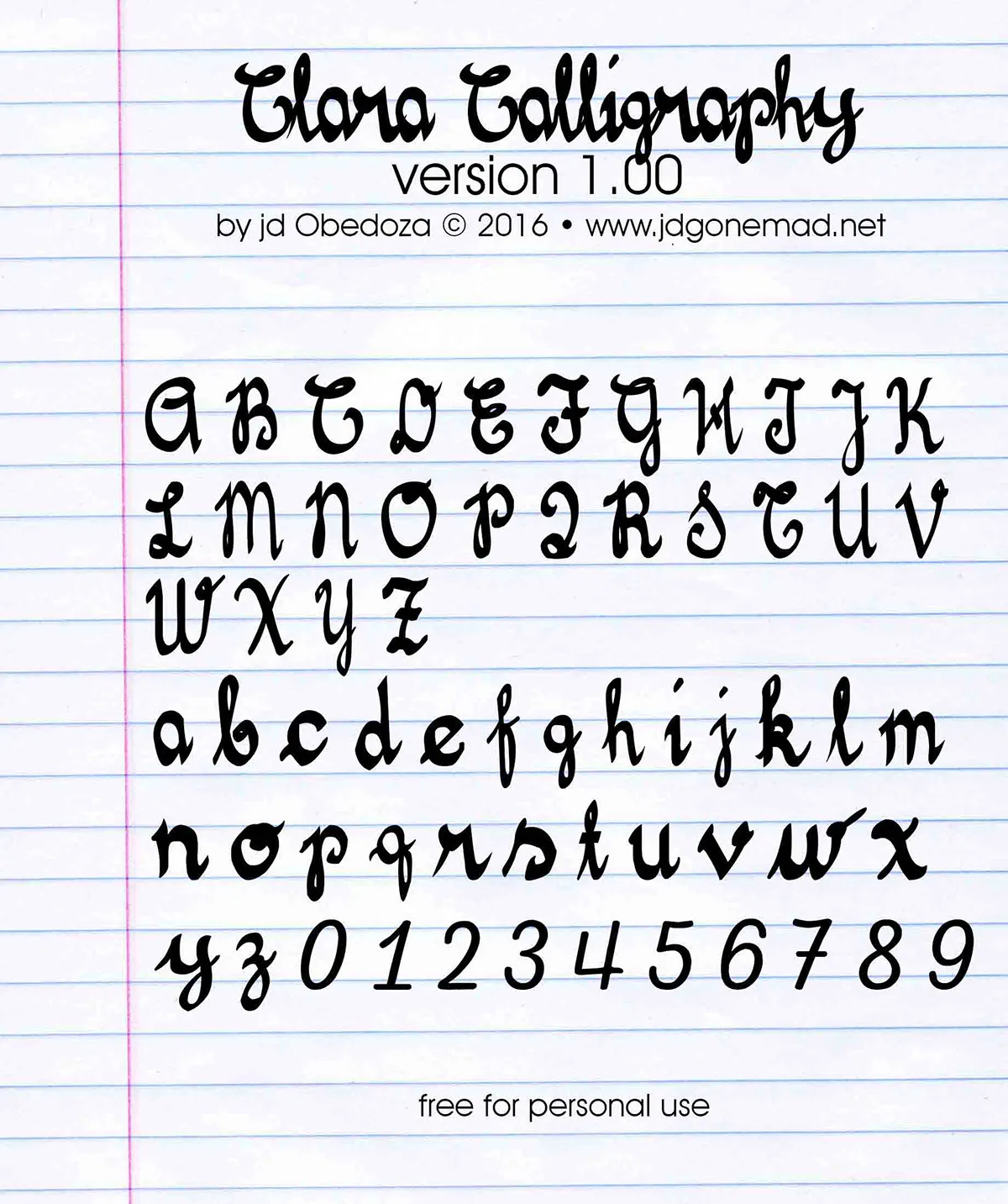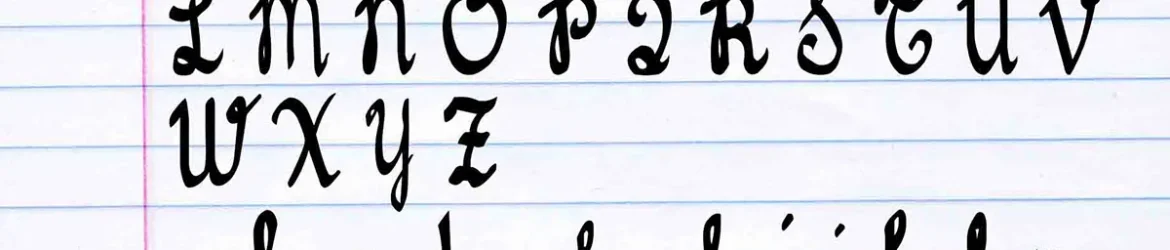
Clara Calligraphy Font – Download Grátis
A fonte Clara Calligraphy é inspirada na escrita à mão da filha do designer Hamilton. Este tipo de fonte retrata a caligrafia natural e quase autêntica que as crianças adotam quando escrevem, expressando uma conexão ímpar entre o mundo infantil e o universo dos recursos gráficos. A Clara Calligraphy representa um elo entre a arte da escrita à mão tradicional e os tempos modernos, permitindo que qualquer designer ou criador de materiais use esse tipo para manusear textos com uma elegância e sofisticação perfeitas. É a escolha ideal para trabalhos de design gráfico, identidades corporativas, artigos publicitários e até mesmo elementos de web personalizados, oferecendo um toque autêntico que enriquece qualquer projeto.